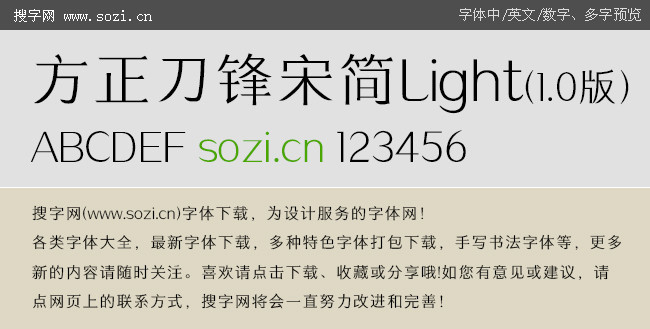
方正刀鋒宋簡Light1.0
搜字網提供一款方正刀鋒宋簡Light1.0中文字體下載,方正刀鋒宋簡是一款漂亮的宋體字體。由方正字庫全新開發的一款非常不錯的中文字體,該字體基于宋體而開發的,在宋體中的字角加入了銳利感,整體效果出色,適合書籍排版,海報設計,包裝設計等應用。(本字體為個人非商用版,如需要商用請聯系方正公司購買版權)